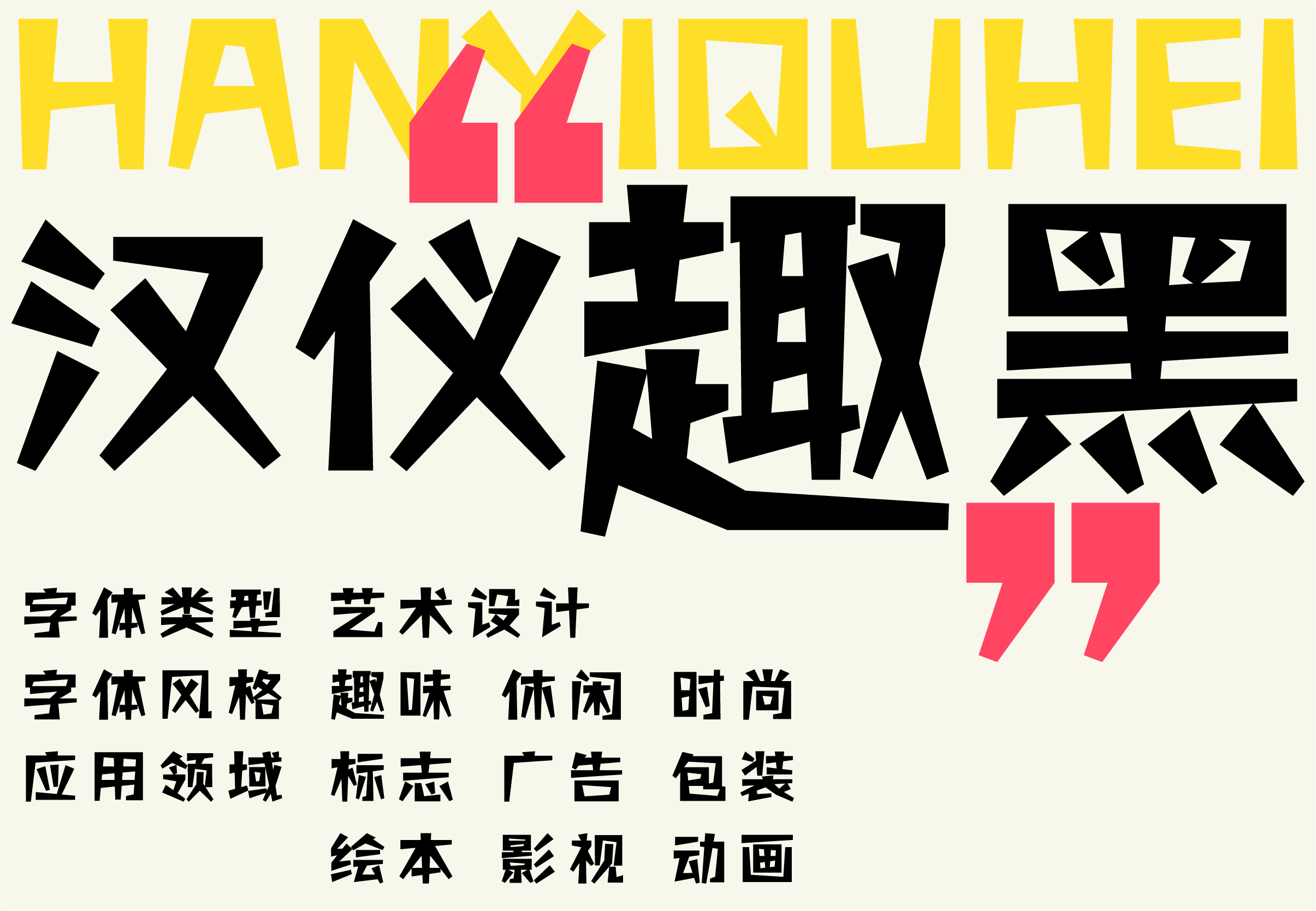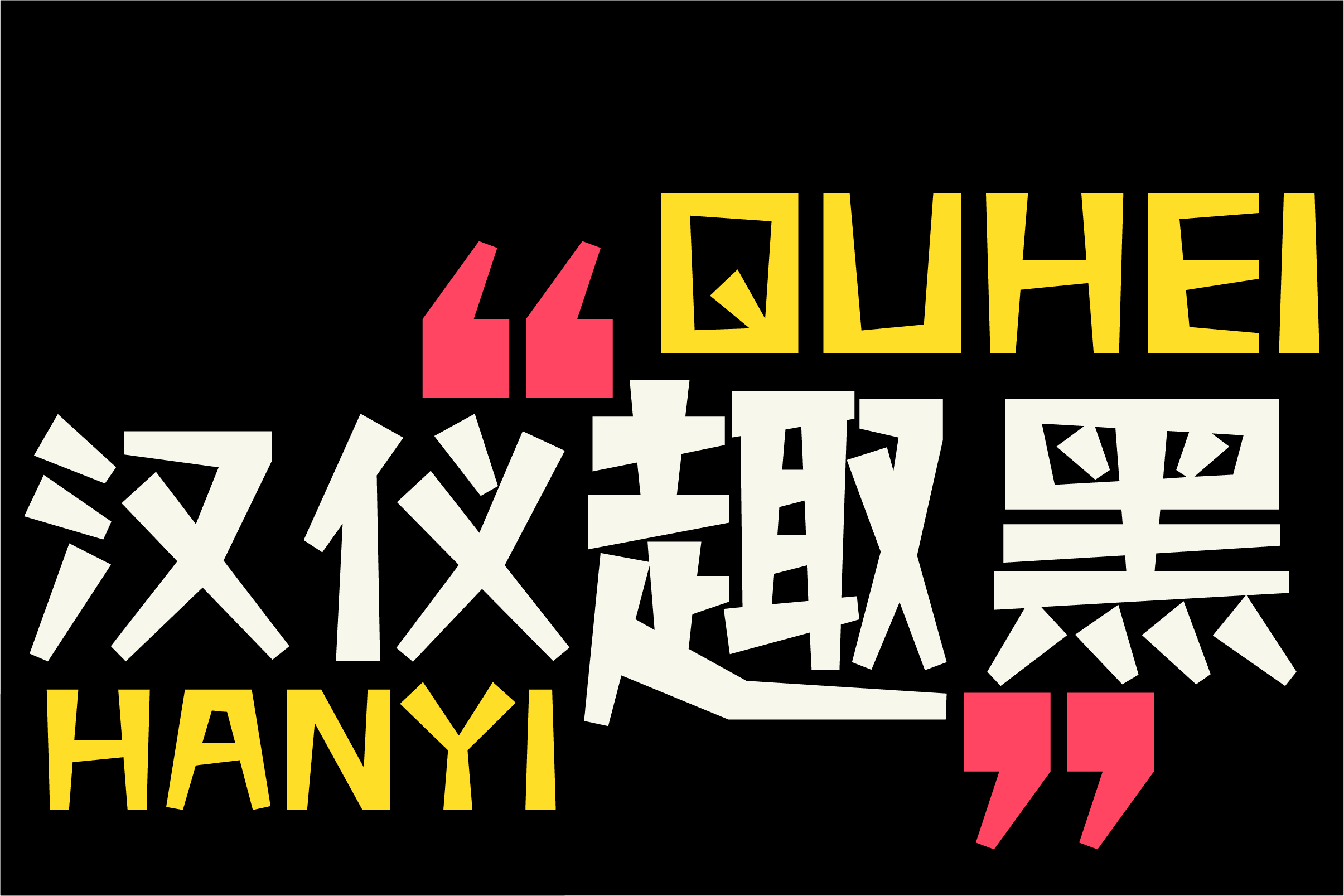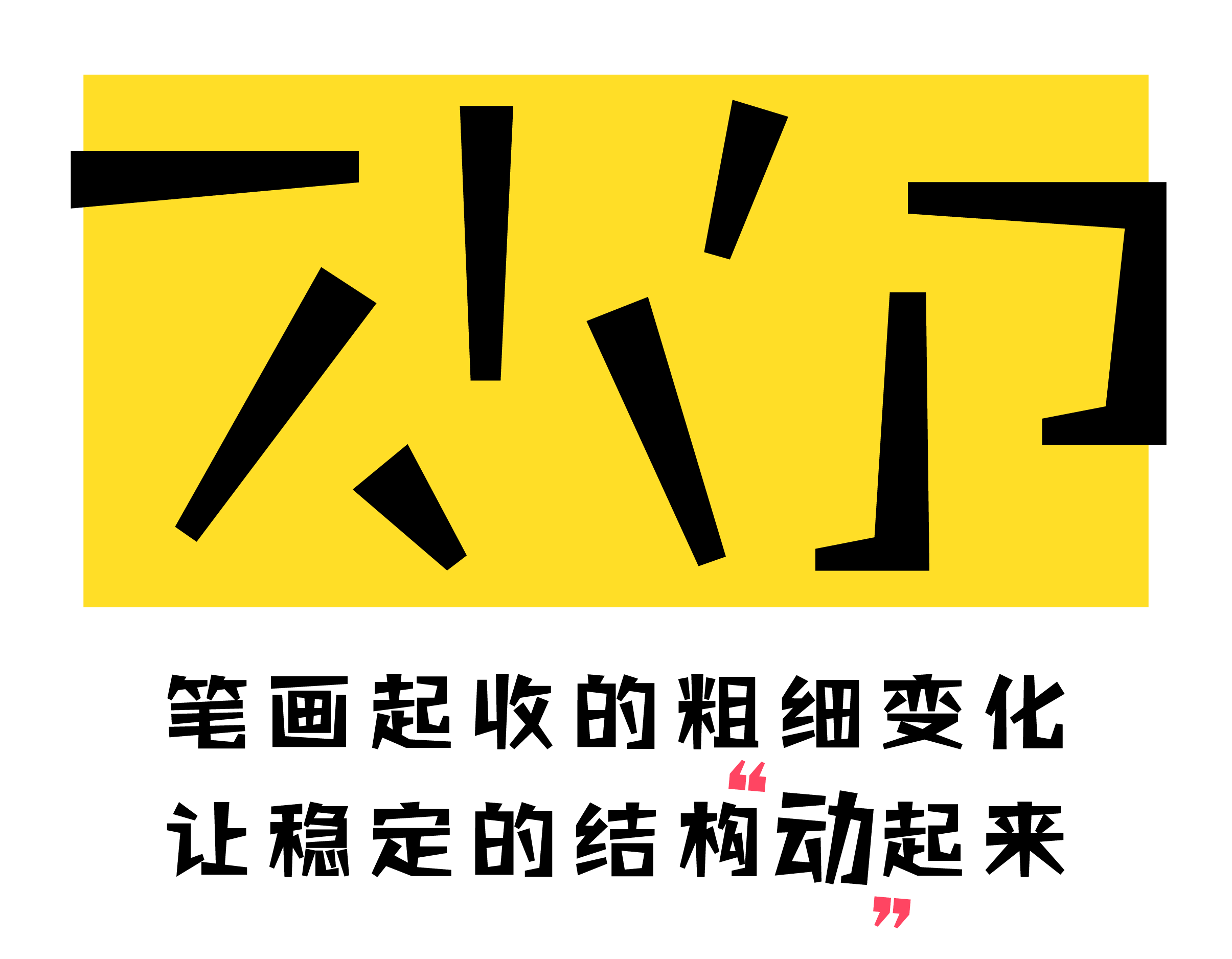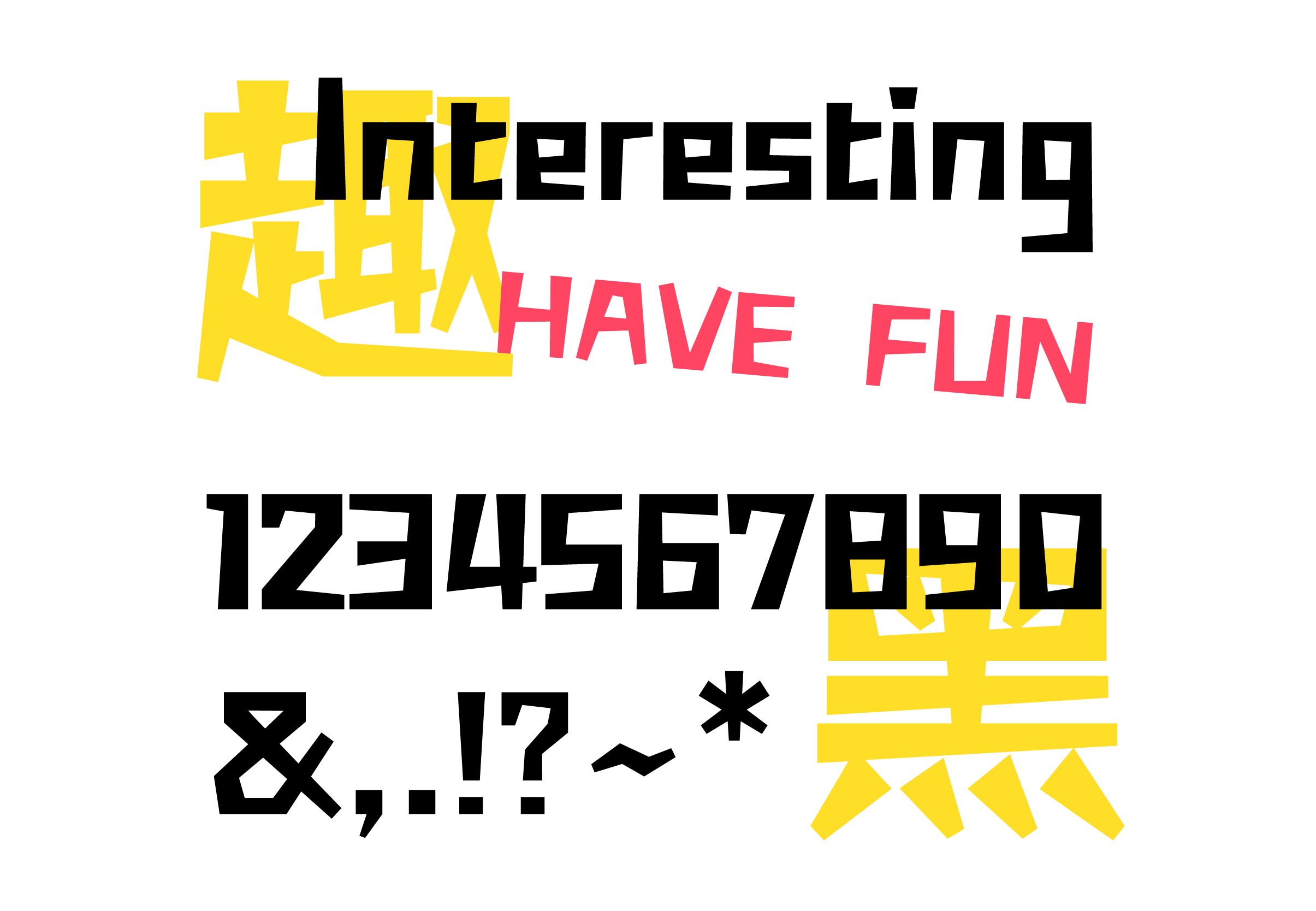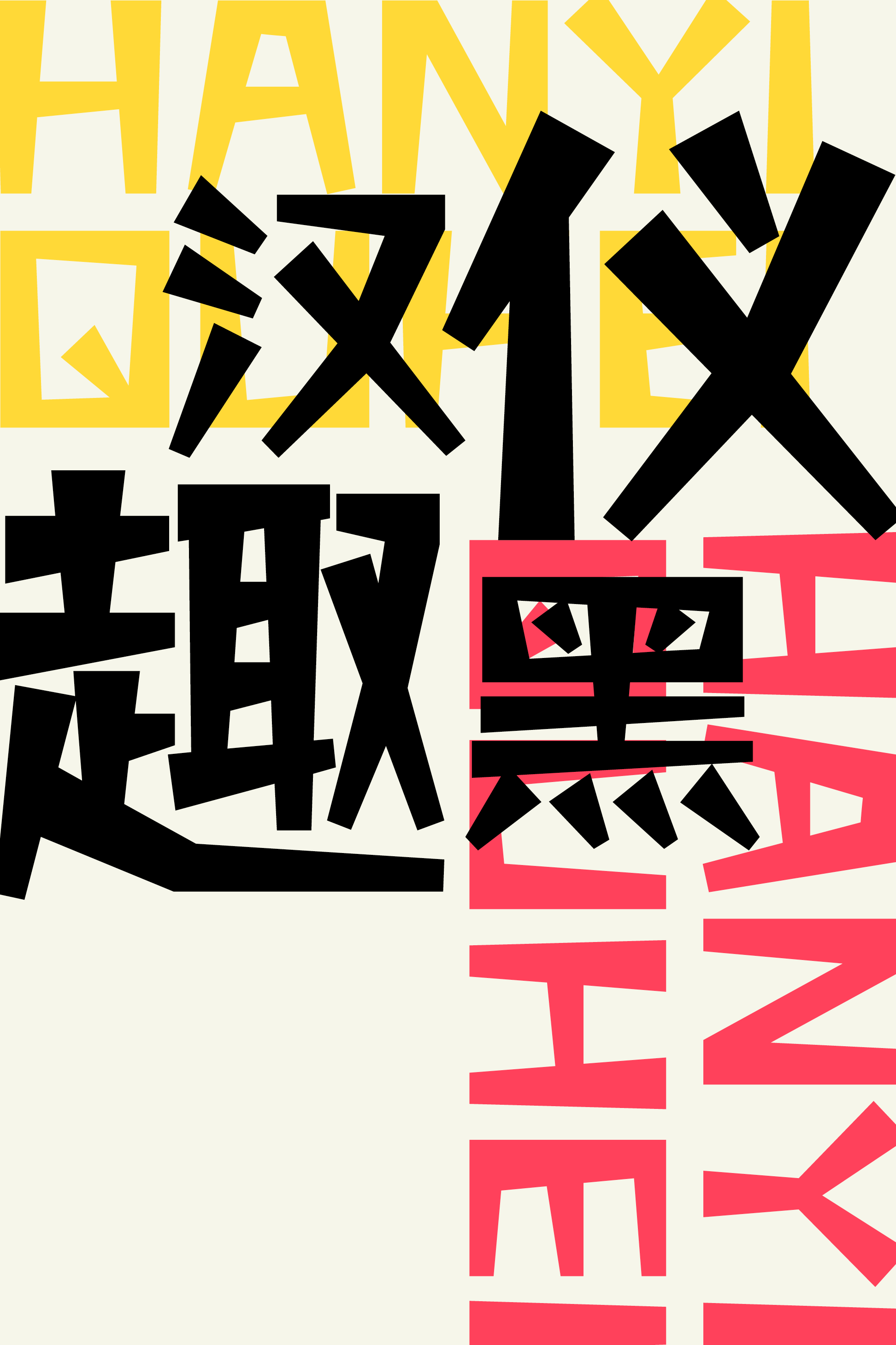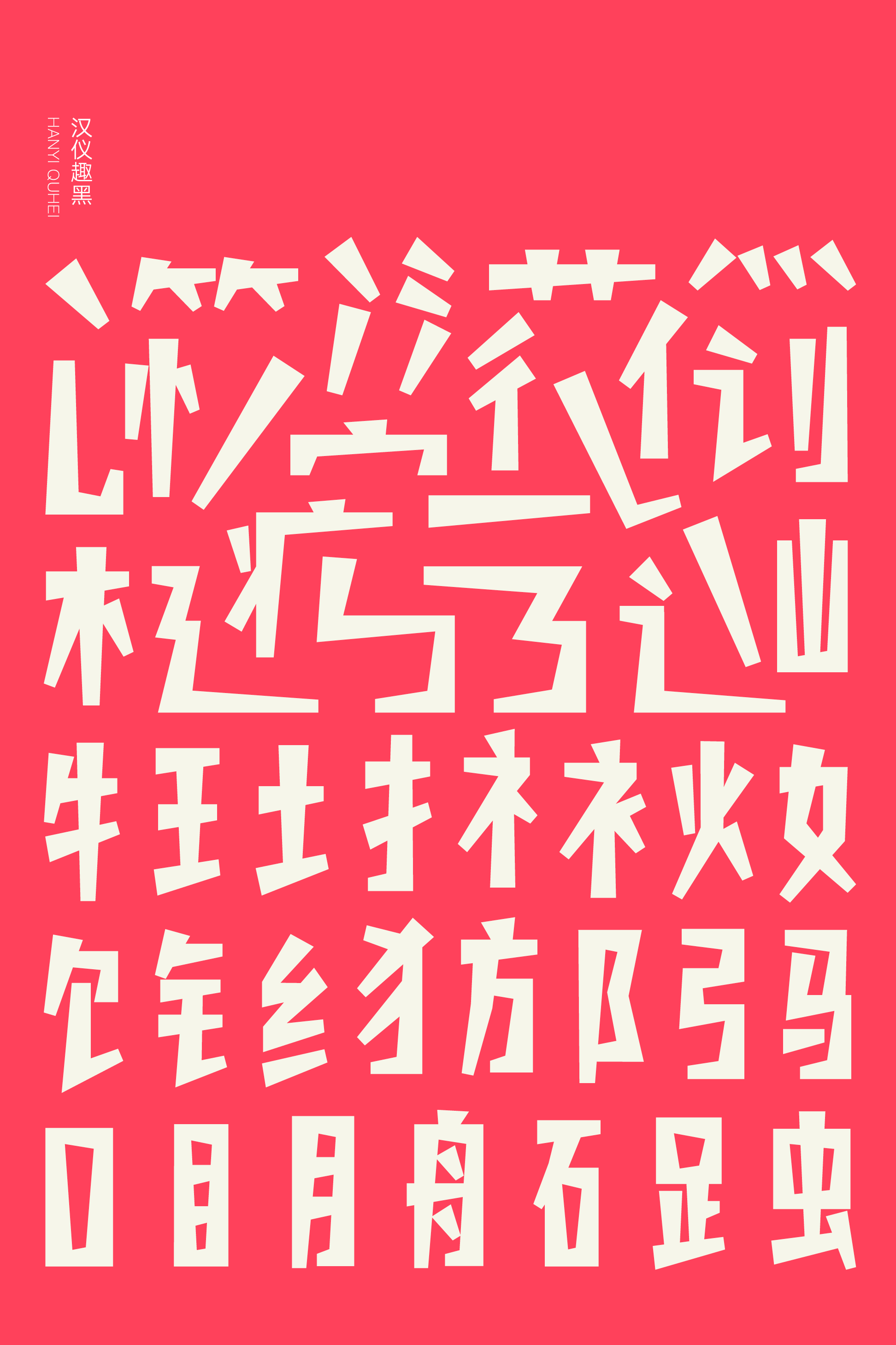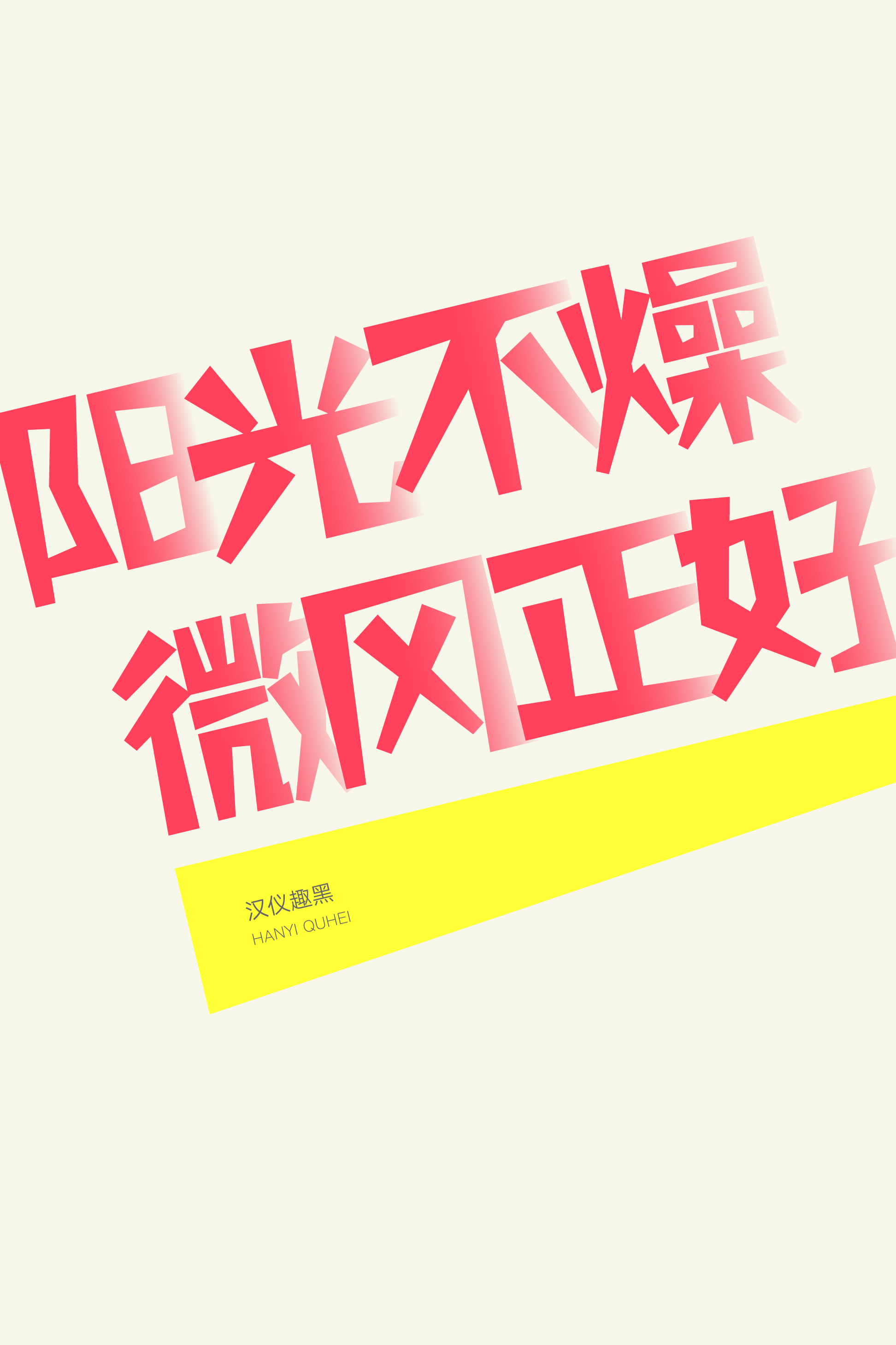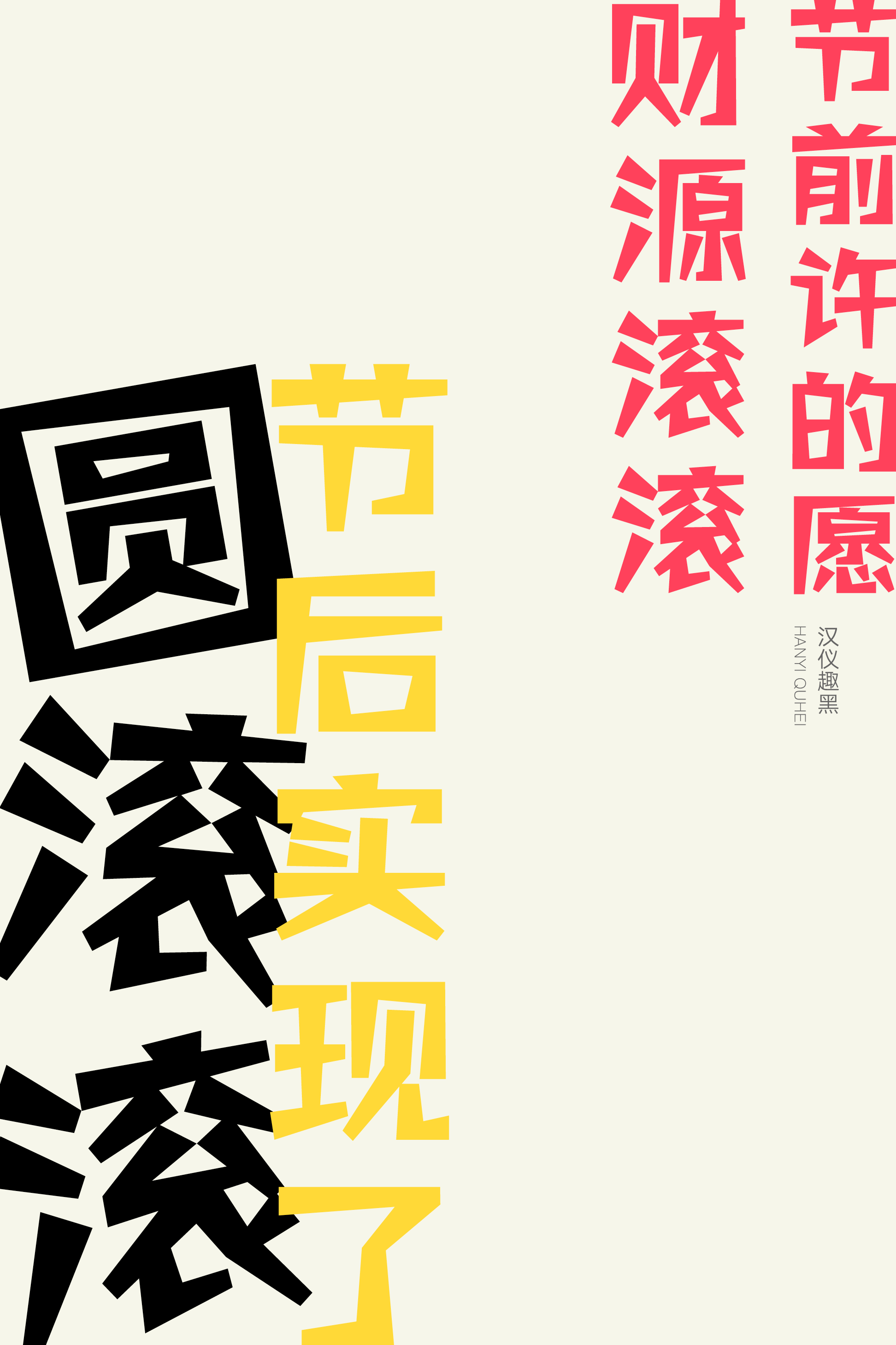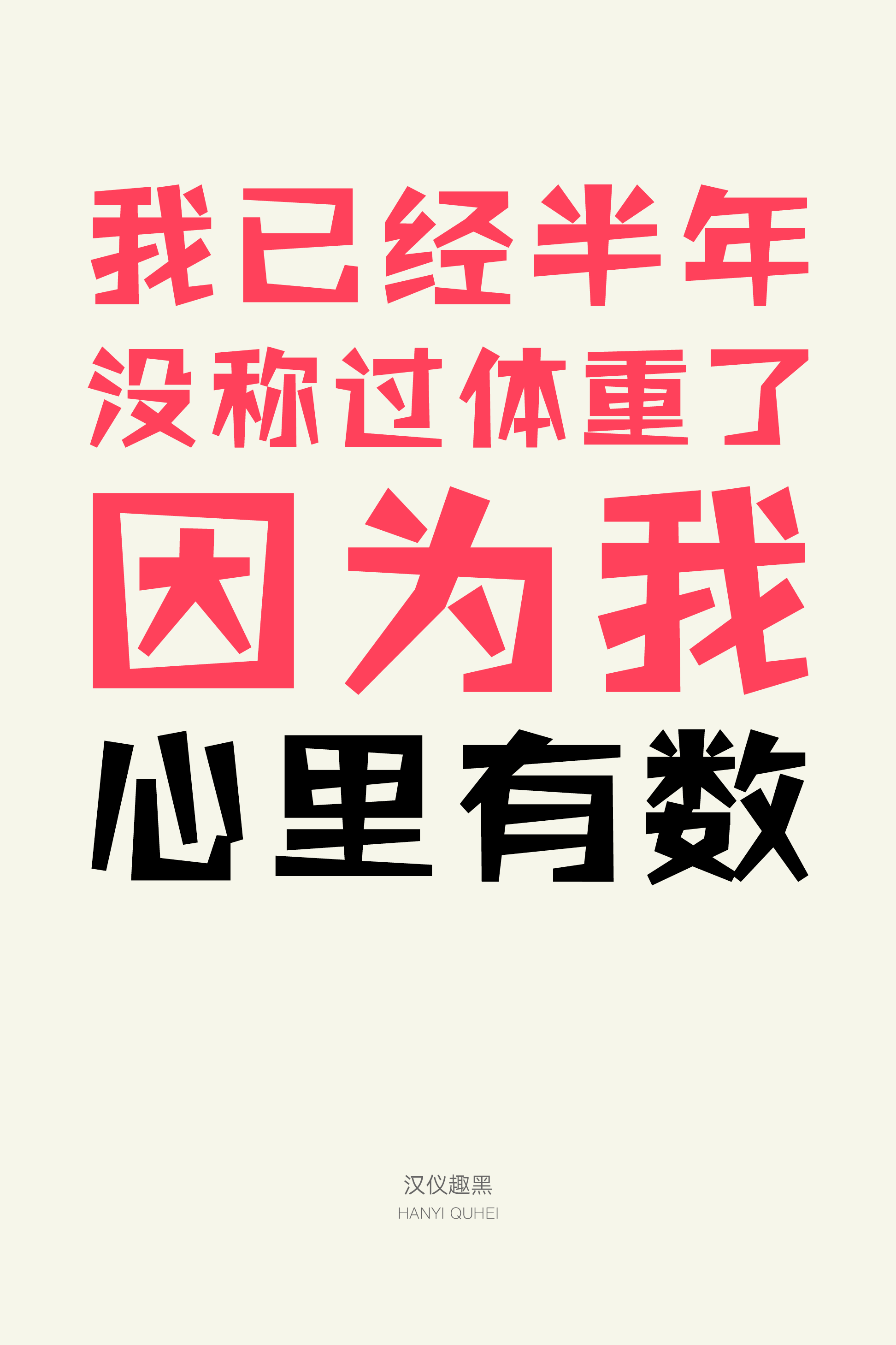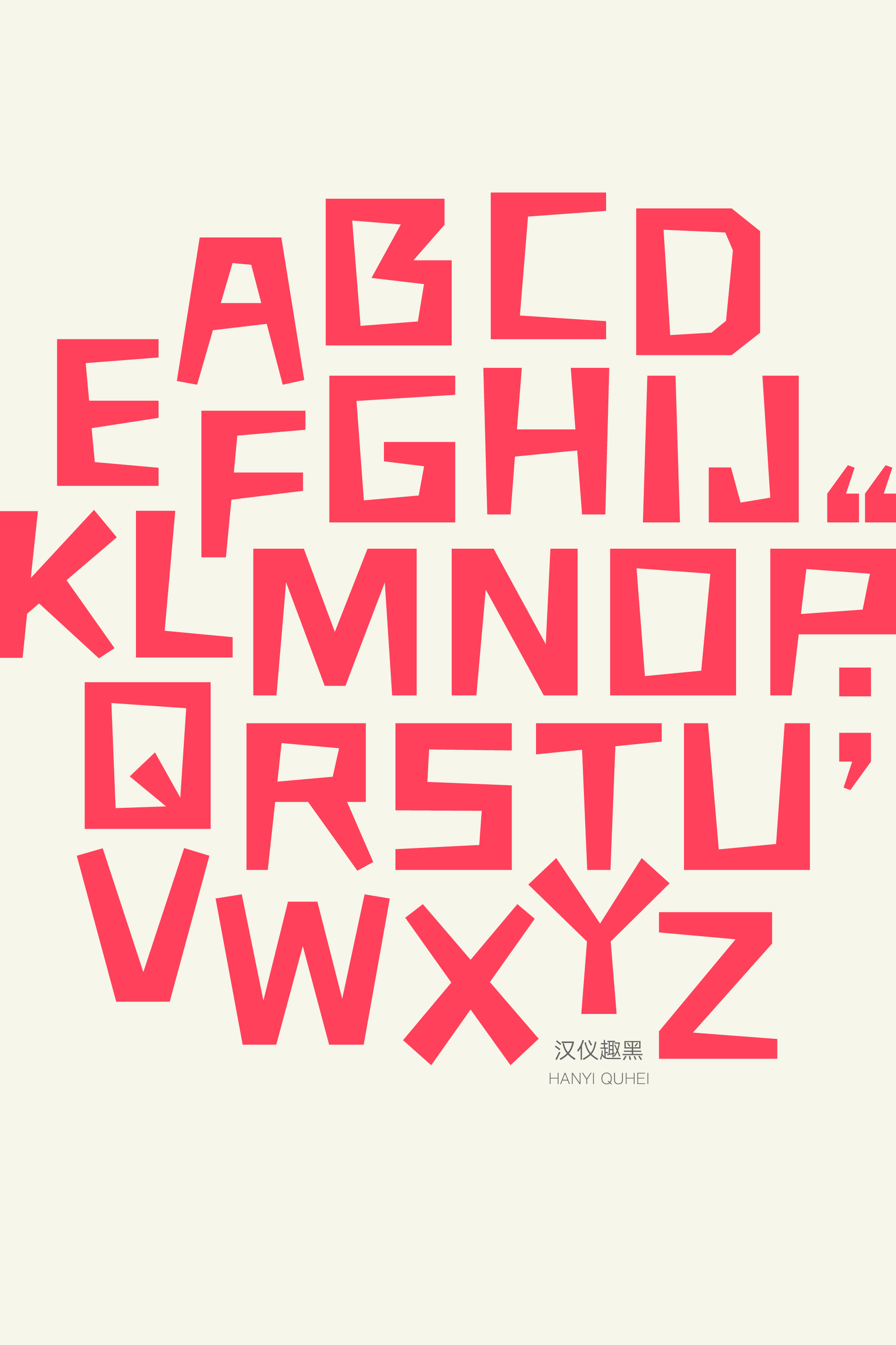
汉仪趣黑
汉仪趣黑,趣味不走寻常路!以黑体为基础,结构稳定。直来直往的笔画富于粗细变化,灵活而有规律。这款字体稳重中略带调皮趣味,适合作为标题字体应用于电商广告、影视娱乐、游戏动画等多种使用场景,给排版带来有趣的小惊喜。
以正方的黑体为基础,造型稳定。
笔画直来直往,干脆利落。
笔画的粗细变化灵活而有规律。
西文部分同样以方直的线条构成,生动有趣。